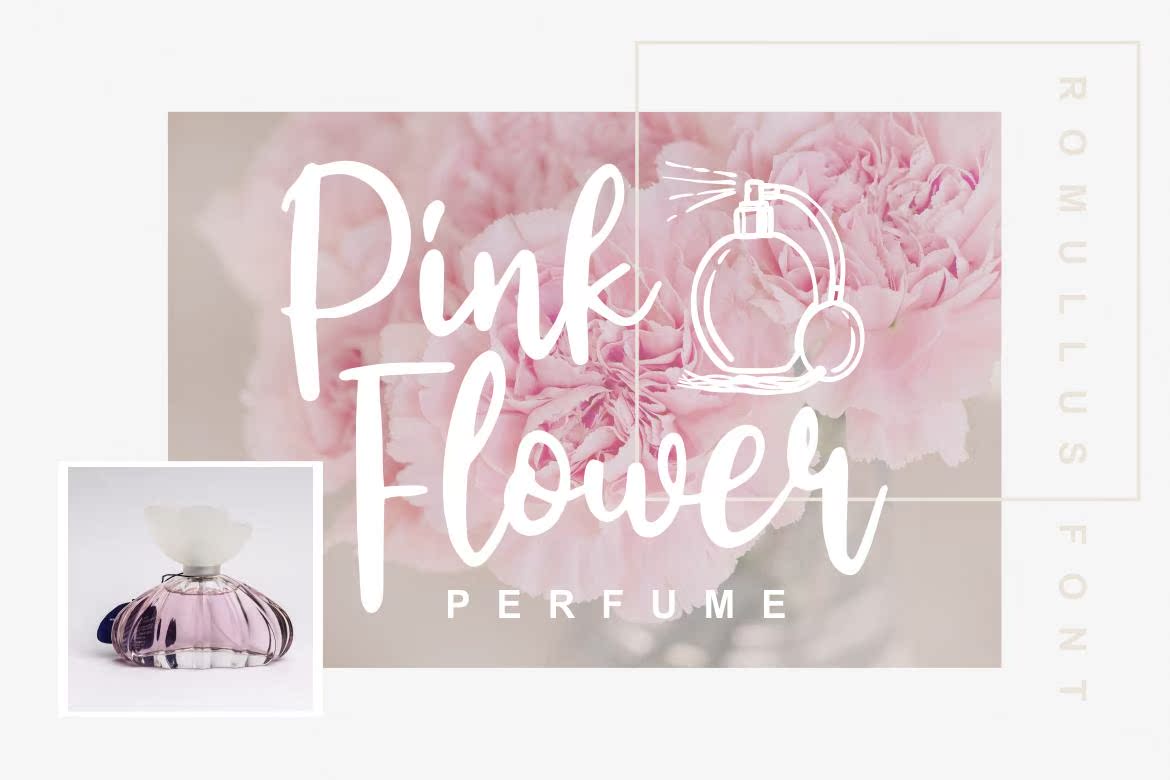
每个人,,,,简介“Romullus”的字体都是很好的脚本字体。通过连字,你可以让这个字体更漂亮、好玩、优雅和自然。这个脚本集完美地体现了博客、品牌、杂志、海报、文具设计、名片和其他。你得到了什么?–Romullus字体(otf、ttf)感谢你对MyShop的关注!如果您有任何疑问,请随时发送邮件!每个人,,,,简介“Romullus”的字体都是很好的脚本字体。通过连字,你可以让这个字体更漂亮、好玩、优雅和自然。这个脚本集完美地体现了博客、品牌、杂志、海报、文具设计、名片和其他。你得到了什么?–Romullus字体(otf、ttf)感谢你对MyShop的关注!如果您有任何疑问,请随时发送邮件!